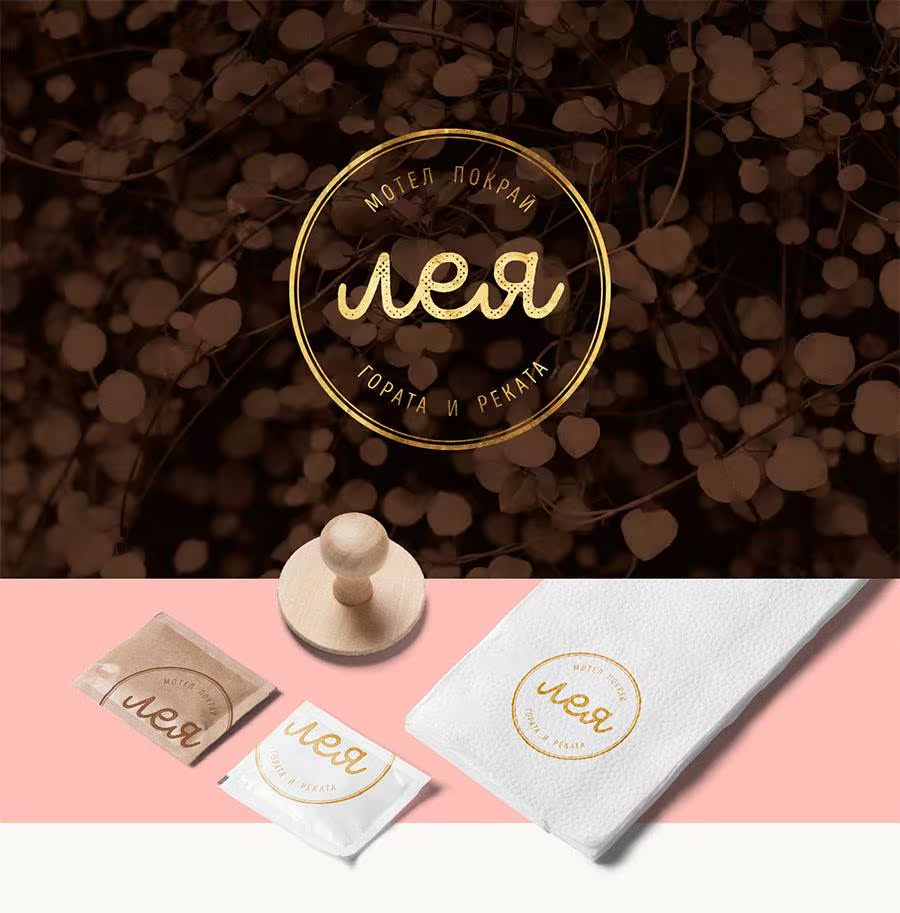
Intro Rust 包括 4 个子系列——Intro Rust、Intro Script、Intro Head 和 Intro Goodies。它可用于创建几乎所有类型的设计项目,如印刷材料和网页设计。只需发挥您的想象力,使用其中一种 Intro Rust 字体,您的项目就会变得比以往任何时候都更加生动活泼。